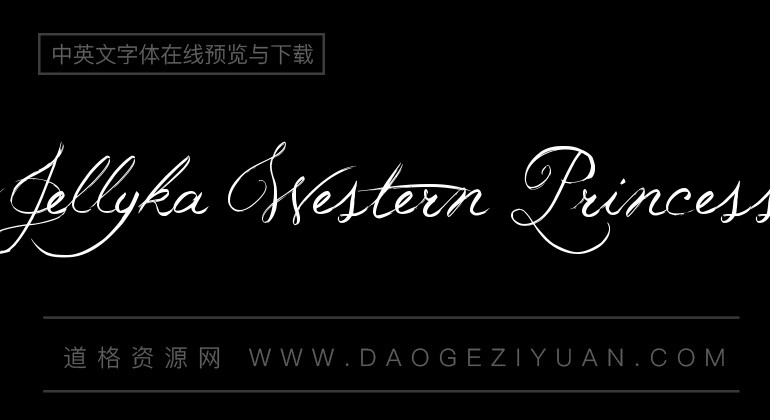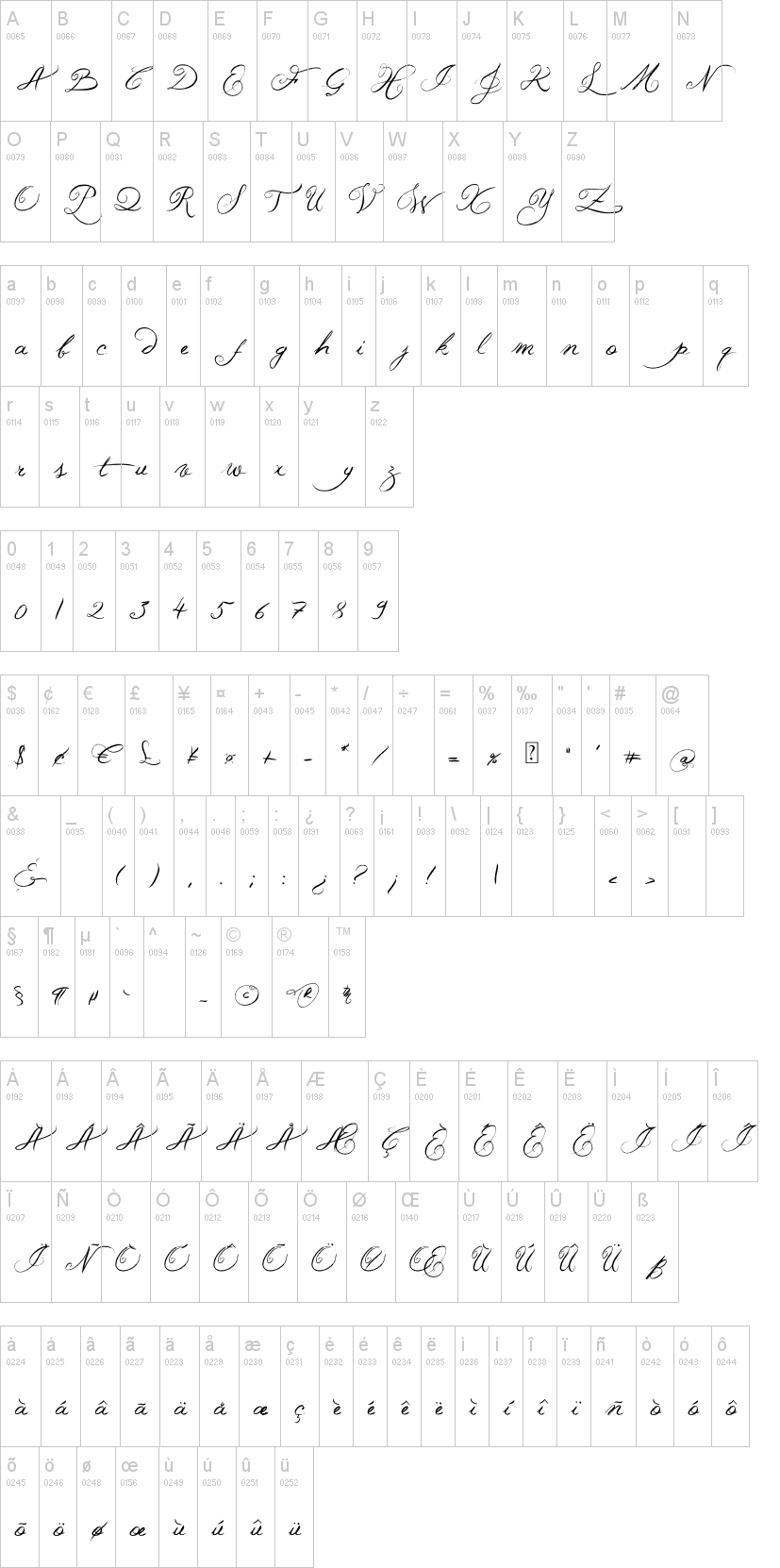
Jellyka Western Princess
? Jellyka Western Princess 字体是一款拥有浓郁西部风情的手写体字体,它的特点是具有浓浓的复古西部风格,字体细腻柔和,线条细腻,充满活力,充满乡村情调,极富表现力,适用于拼贴画、海报设计、书法绘画等各类艺术创作。
Jellyka Western Princess是一款非常不错的手写艺术字体,具有很好的视觉感,适合于文化类的宣传设计、商业类品牌的广告和产品包装设计以及个性化文字排版等较多场景。